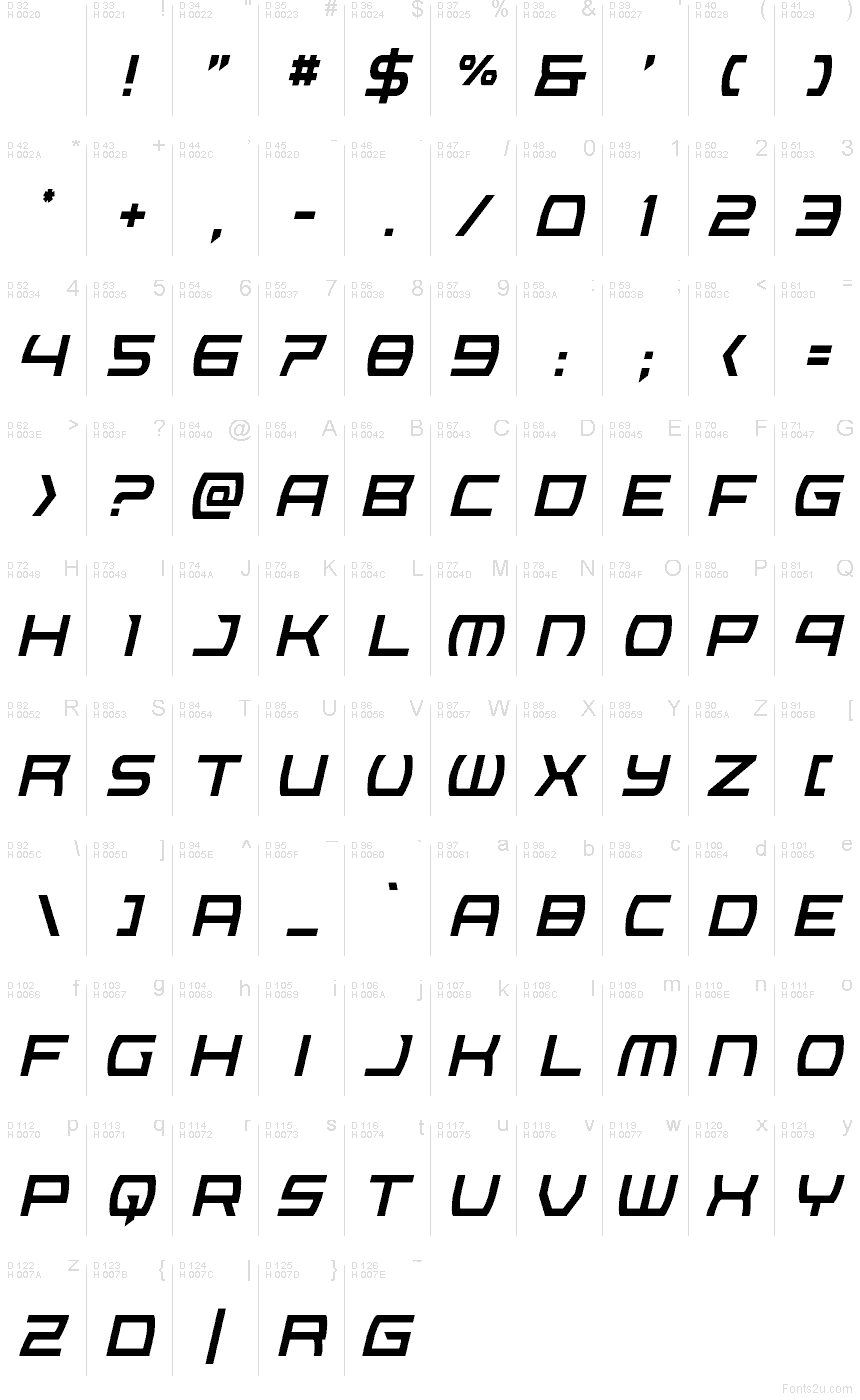
Icemaster Condensed Italic von Iconian Fonts ist eine kostenlose, futuristische Display-Schrift, die mit ihrer scharfen, dynamischen Anmutung an Sci-Fi-Logos und die Titel-Typografie der Arcade-Ära erinnert. Die Großbuchstaben vermitteln durch ihre abgeschnittenen Winkel, den engen Zeilenabstand und die kräftigen Striche pure Bewegung – als wären sie maschinell gefertigt und nicht von Hand gezeichnet.
Sie eignet sich ideal für Poster-Überschriften, Game-Branding, Comic-Cover, Action-Titel und Merchandising-Grafiken, bei denen die Schrift Schnelligkeit und kühle Präzision auf einen Blick vermitteln soll. Da die Buchstaben kompakt und stark geneigt sind, funktioniert sie hervorragend für kurze Namen, Team-Logos und markante Titelzeilen, die einen eleganten, druckvollen Look benötigen.
Icemaster Condensed Italic